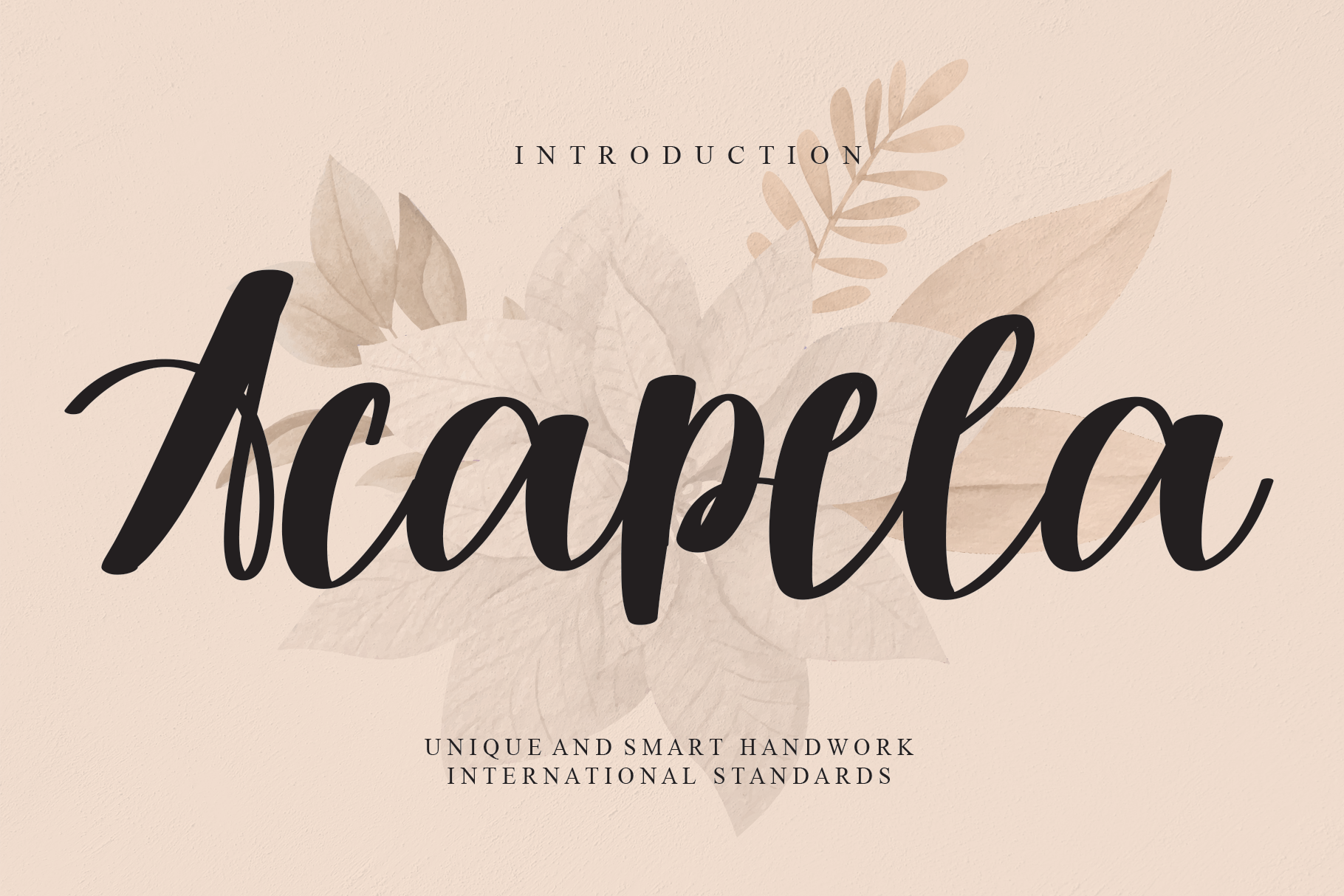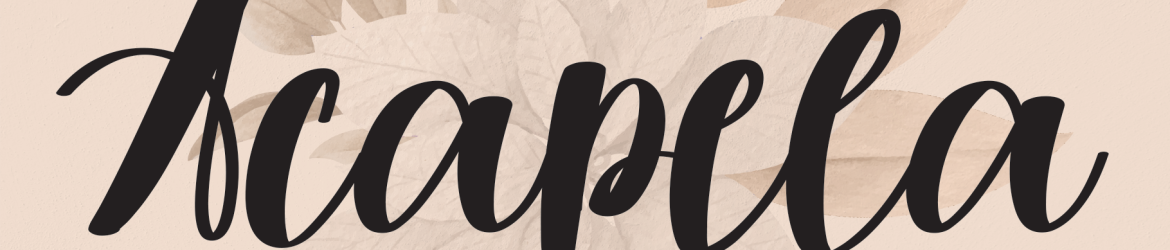
Acapela Font é uma elegante fonte escrita a mão que transmite delicadeza e felicidade. Com traços leves e finos, ela se adequa perfeitamente para cartões de aniversário, convites de casamento ou qualquer projeto gráfico que exige um toque romântico e personalizado. Esta fonte é ideal para dar uma aposta única a seus projetos digitais, oferecendo uma textura natural que combina perfeitamente com qualquer design editorial. Com sua versão handwritten da Acapela Font, você pode explorar maneiras diferentes de expressar seu estilo pessoal em documentos importantes ou simplesmente na criação de cartões e mensagens personalizadas.